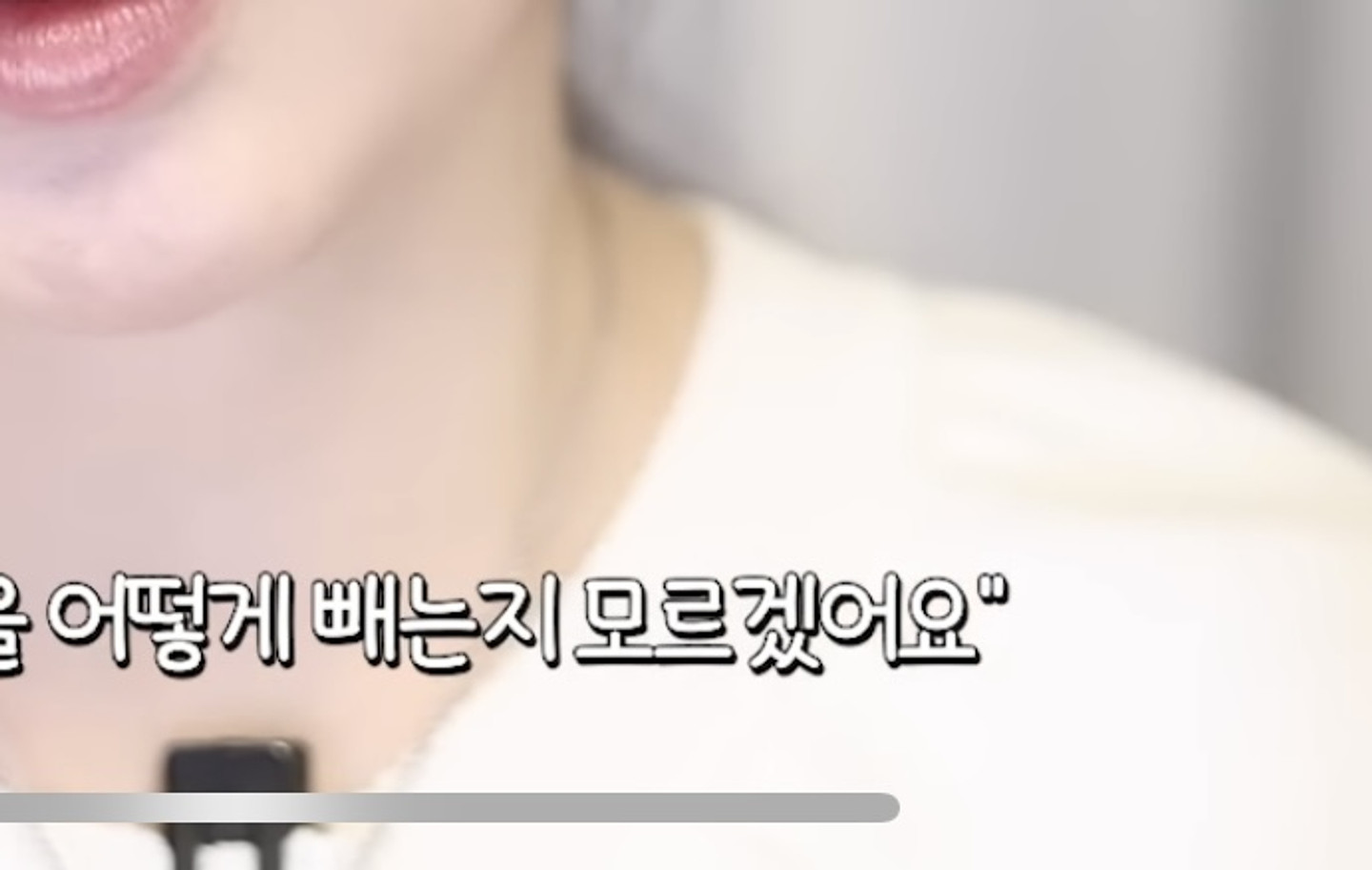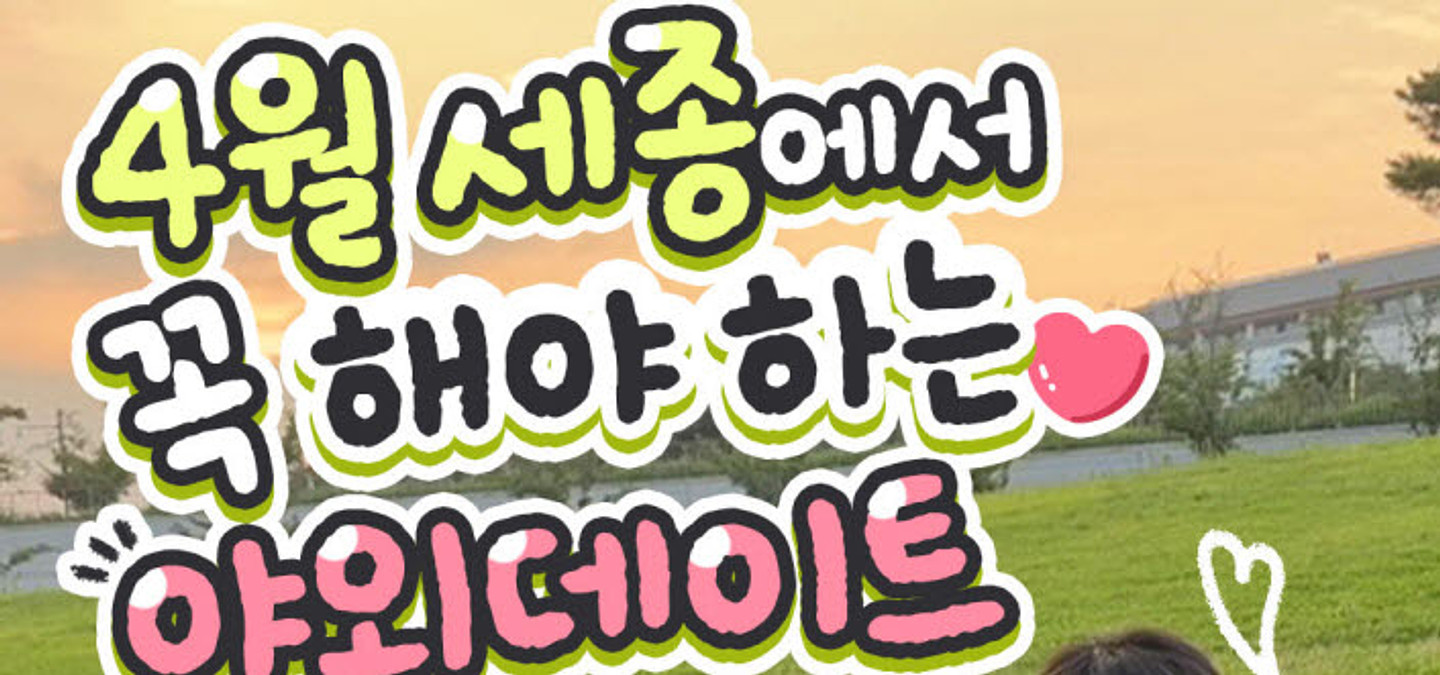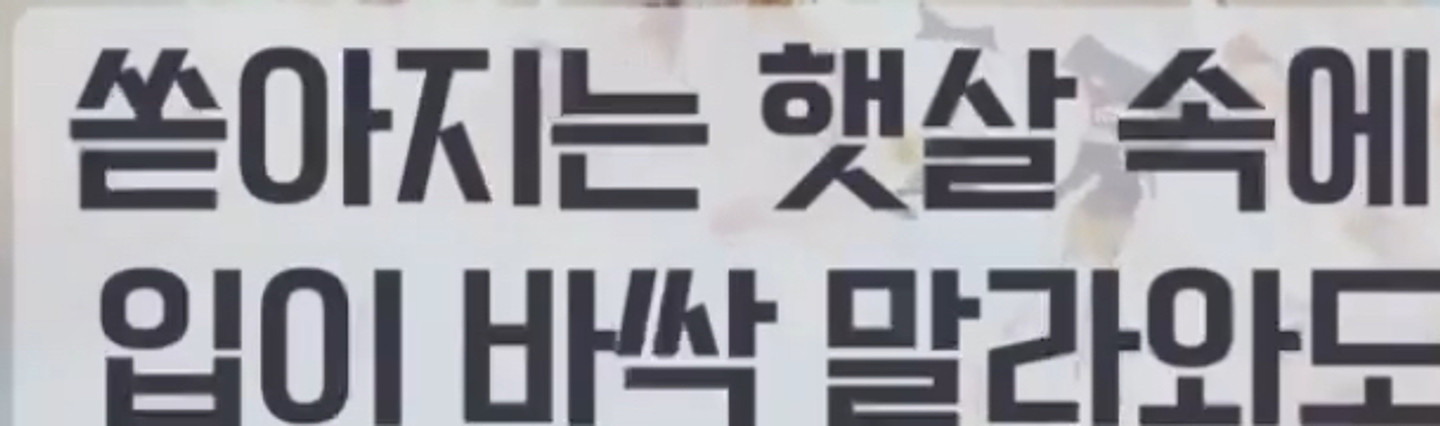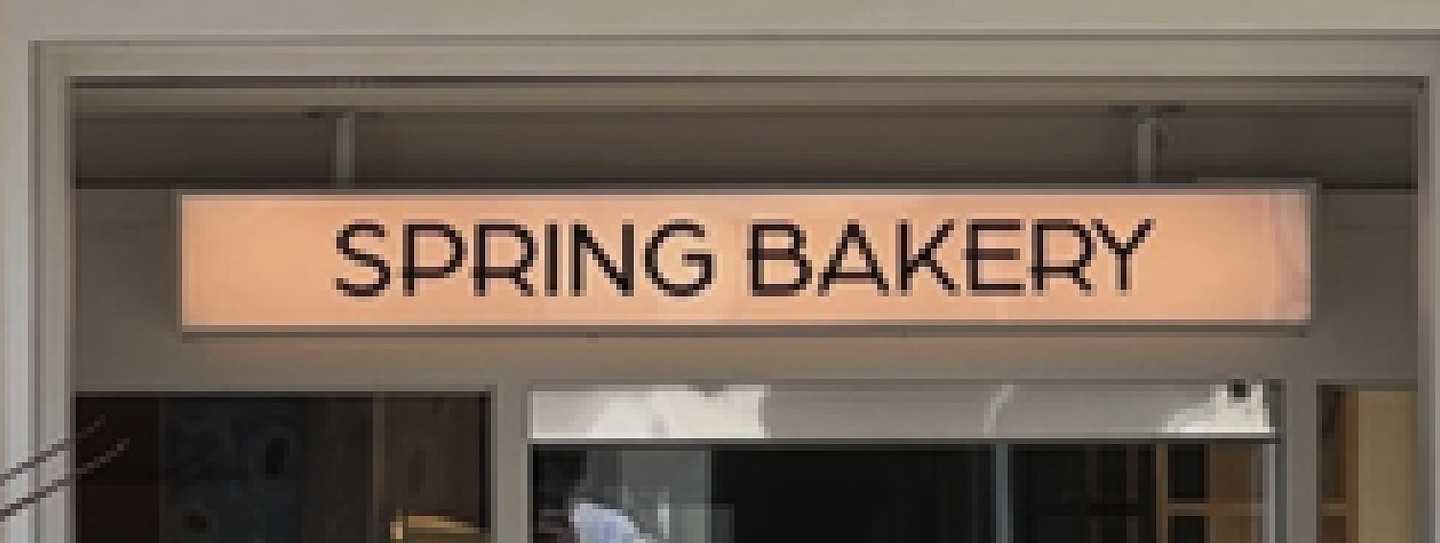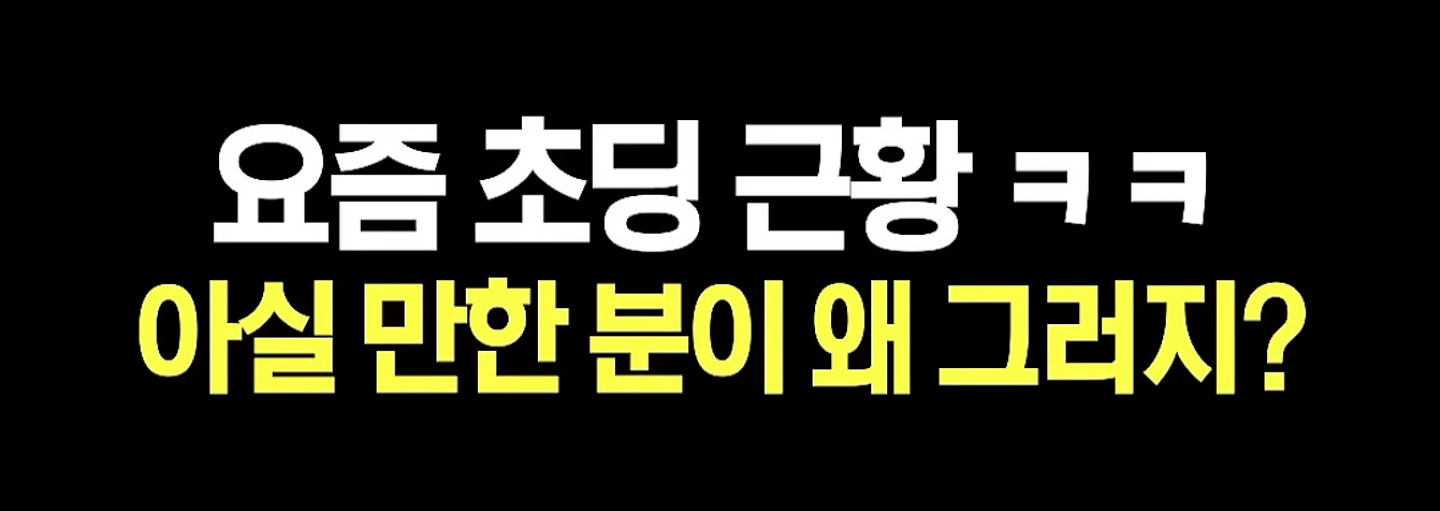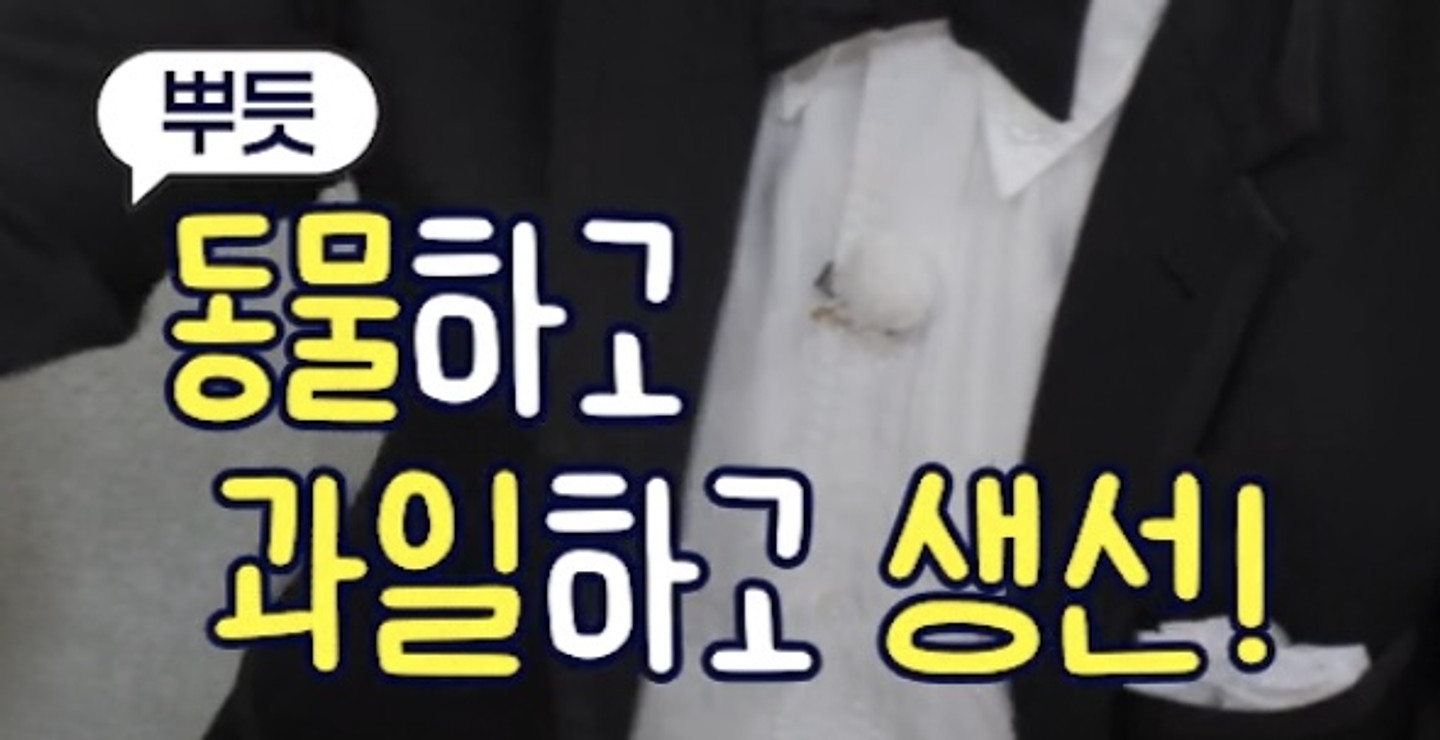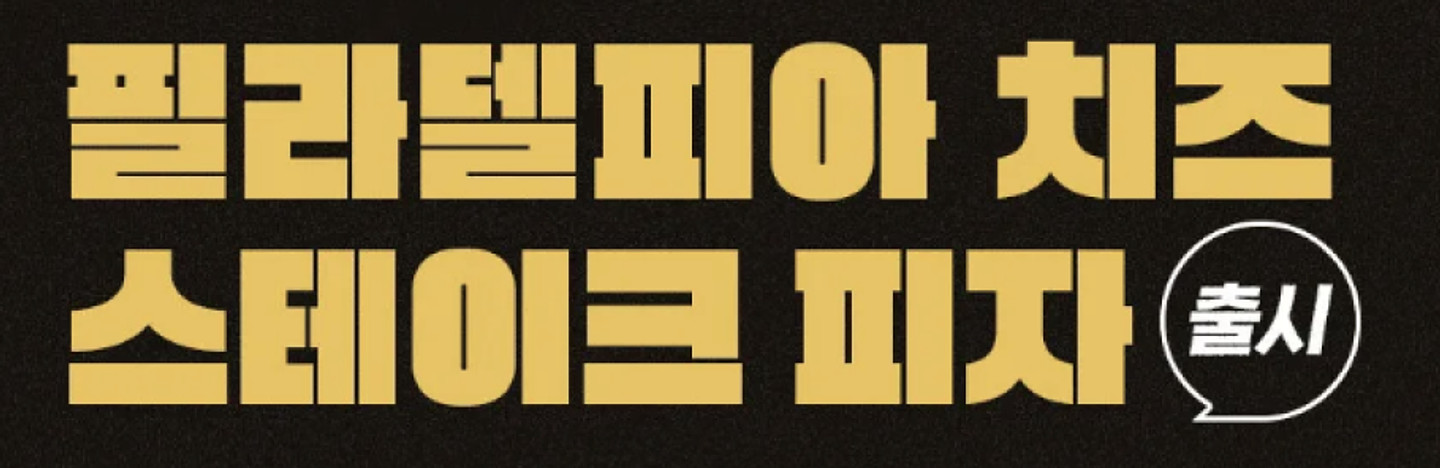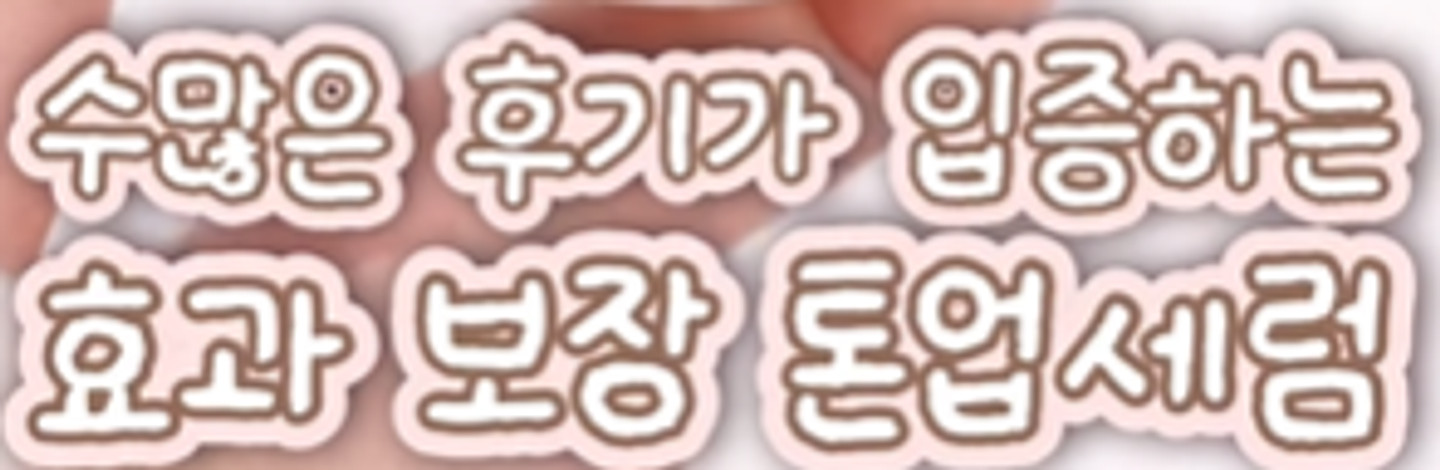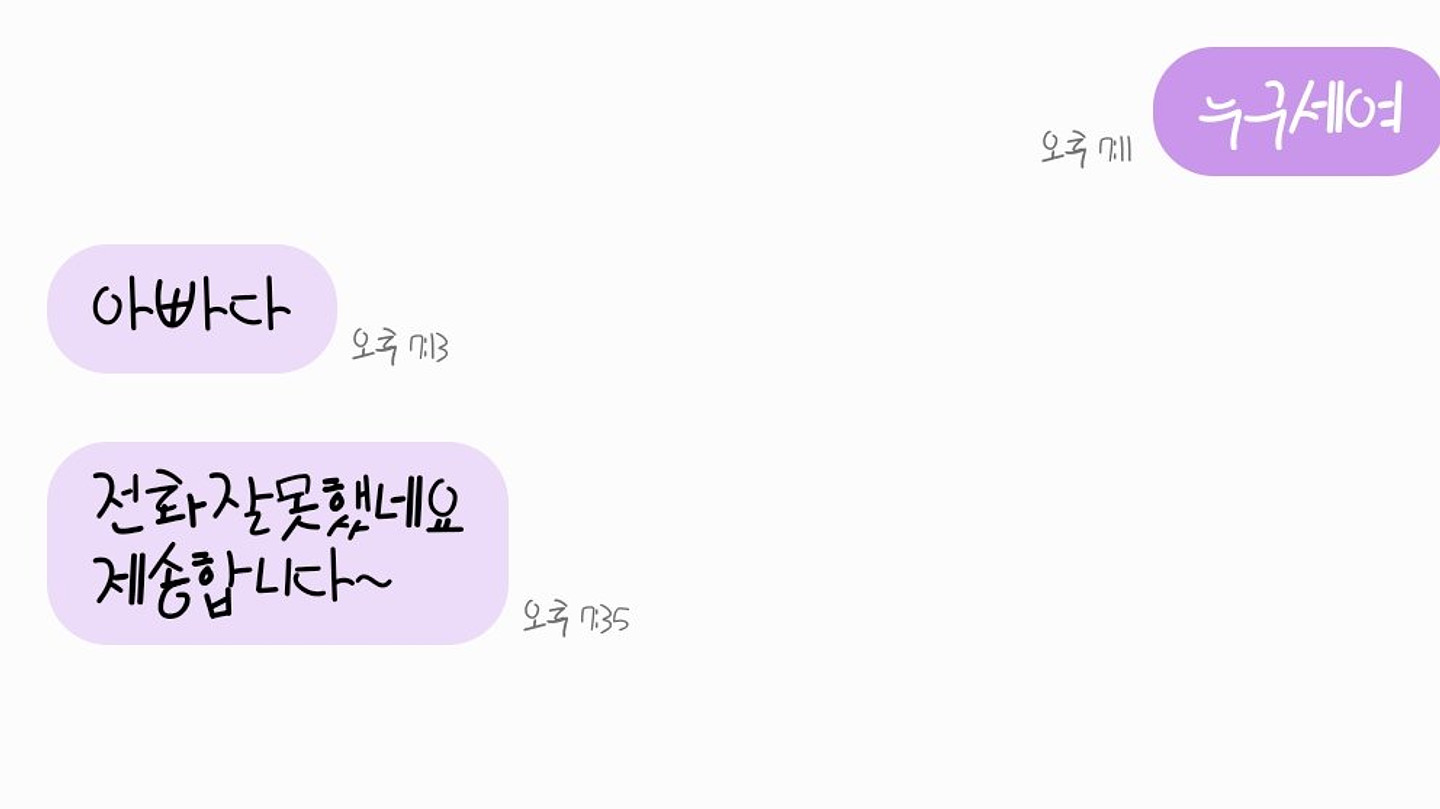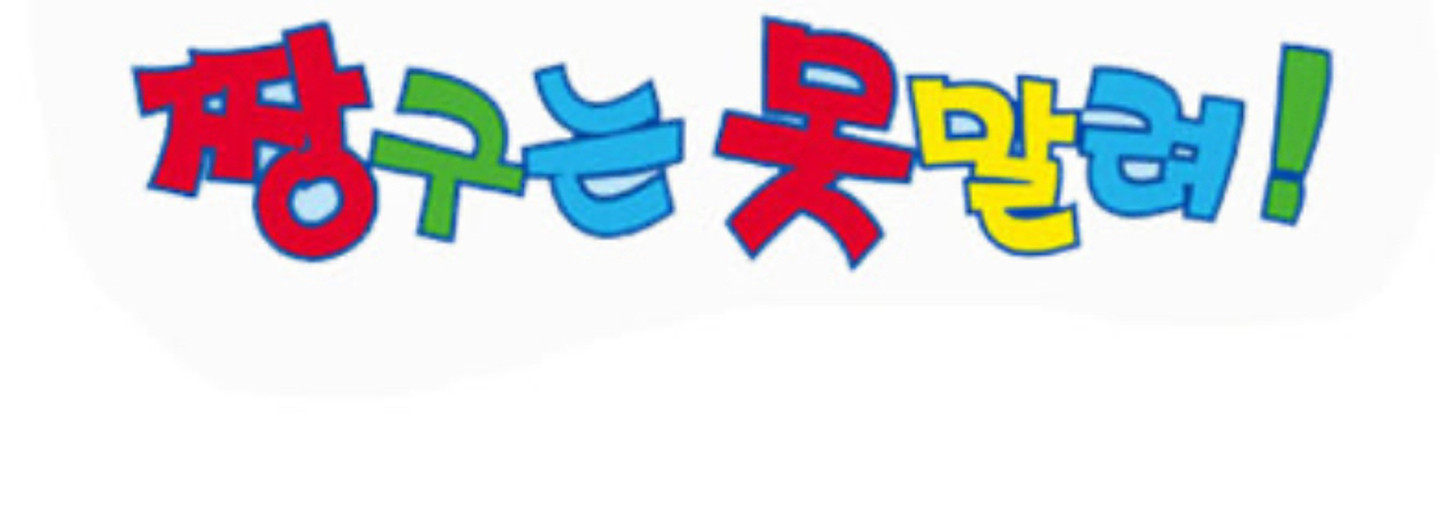
이건 무슨 폰트인가요?
이 폰트 궁금합니다! ㅜㅜ
어떤 폰트인지 알고 싶습니다! 영문 폰트입니다.
이 폰트 궁금해요~~
이 폰트 아시는 분 ㅠㅠ
'3월 1일 만세를 외쳐요' 부분 폰트 이름이 궁금합니다
아침달 시집 본문입니다. 사진으로 검색해봤는데 잘 모르겠더라구요ㅠㅠ
폰트 이름이 궁금합니다!
안녕하세요! 이 폰트 어떤거일까용! 캡컷에 있는 것 같긴 한데ㅠㅠ 답변주시면 너무 감사하겠습니다
사주아이 홈페이지 폰트가 군금해요
폰트 끝이 둥글둥글한 고딕 같은데요. 뭘까요?
애플 드라마 예고편 자막인데 무슨 폰트일까요? 그냥 고딕체라고 하기엔 약간 균형이 안 맞게 디자인 되어 있어요. 가끔 영화관 가면 저런 폰트 본적도 있는거같고요.. 궁금합니다.
이 폰트 뭔지 아시나요 ㅠ ㅜ
이 폰트 이름이 뭔가요?
알려주세요!
무슨 폰트일까요? 현수막회사에서 쓰는 폰트같은데 뭔지 모르겠네요
어떤 폰트인지 아시는 분 있나요?
이 영문폰트가 뭔지 궁금합니다:)
이거 3같은 거 무슨 폰트에요? 너무 쓰고싶어요 ㅠㅠ
카카오 뱅크 폰트 궁금합니다!
무슨 폰트인지 너무 궁금합니다..!!
폰트 알려주세용
요즘 인스타그램에 릴스에서 자주 보이는 글씨체인거같은데 아무리 찾아도 안나오네요 ㅠㅠ 혹시 아시는분,,,
무슨 폰트일까요??ㅠㅠ
폰트 알려주세요!
이 폰트 무엇인지 궁금해요!
'화색' 폰트 무엇인가요?? ㅇ이 소용돌이처럼 말려 들어가는
이 폰트 뭔가요? 유료폰트라면 이 폰트랑 비슷한 무료폰트 추천도 부탁드립니다ㅜ!!
이 폰트의 이름은 무엇인지요? 유튜브에서 보다가 이뻐서 캡처 했습니다. ^L^
이거 폰트 알려주시면 감사하겠습니다
안녕하세요~ 이거 혹시 어떤 폰트인 지 알 수 있을까요?
혹시 여기 폰트 섞여있을 수도 있나여,,,,
무슨 폰트일까여,,,,,,,
환승연애 인터뷰룸에서 질문할 때 쓰인 폰트 아시는 분 계실까요 ㅠ.ㅠ
큰 타이틀(취업하고싶은데)이랑 아래 서브타이틀(2천만원) 폰트 뭔지 아시는 분 계신가요
ㅇ이 폰트 뭔가요
HOLA 폰트 궁금해요
반듯 길쭉한 폰트
픽셀느낌나는 이 폰트 뭔지 아시는분 계신가요?
이 폰트 이름 부탁드립니다~
이 폰트 이름이 뭐에여?
이 폰트 이름좀 알려주세요
나무위키에서 찾았습니다
이거무슨폰트일까유유유
필기체 같은데 이 글씨체 이름 뭔지 아실까요? 너무 찾고싶어요오오
유튜브 쇼츠 보다가 발견한 폰트인데 예뻐보이네요 오른쪽 윗대각선으로 올라가는 듯한 선이 깔끔해보이는데 어떤 폰트일까요?
폰트 뭔지 궁금해요! 미리 감사합니다
이거 폰트 궁금합니다
드라마 자막인데 무슨 폰트일까요?
이거 무슨 폰트인지 아시는분!
이거폰트뭔가요!?
이 영어 폰트의 이름을 알고 싶어요... 아무리 찾아도 안 나오네요 ㅠ
직사각형에 가까운것 같은데, 무슨 폰트 일까요?
폰트 궁금합니다!!